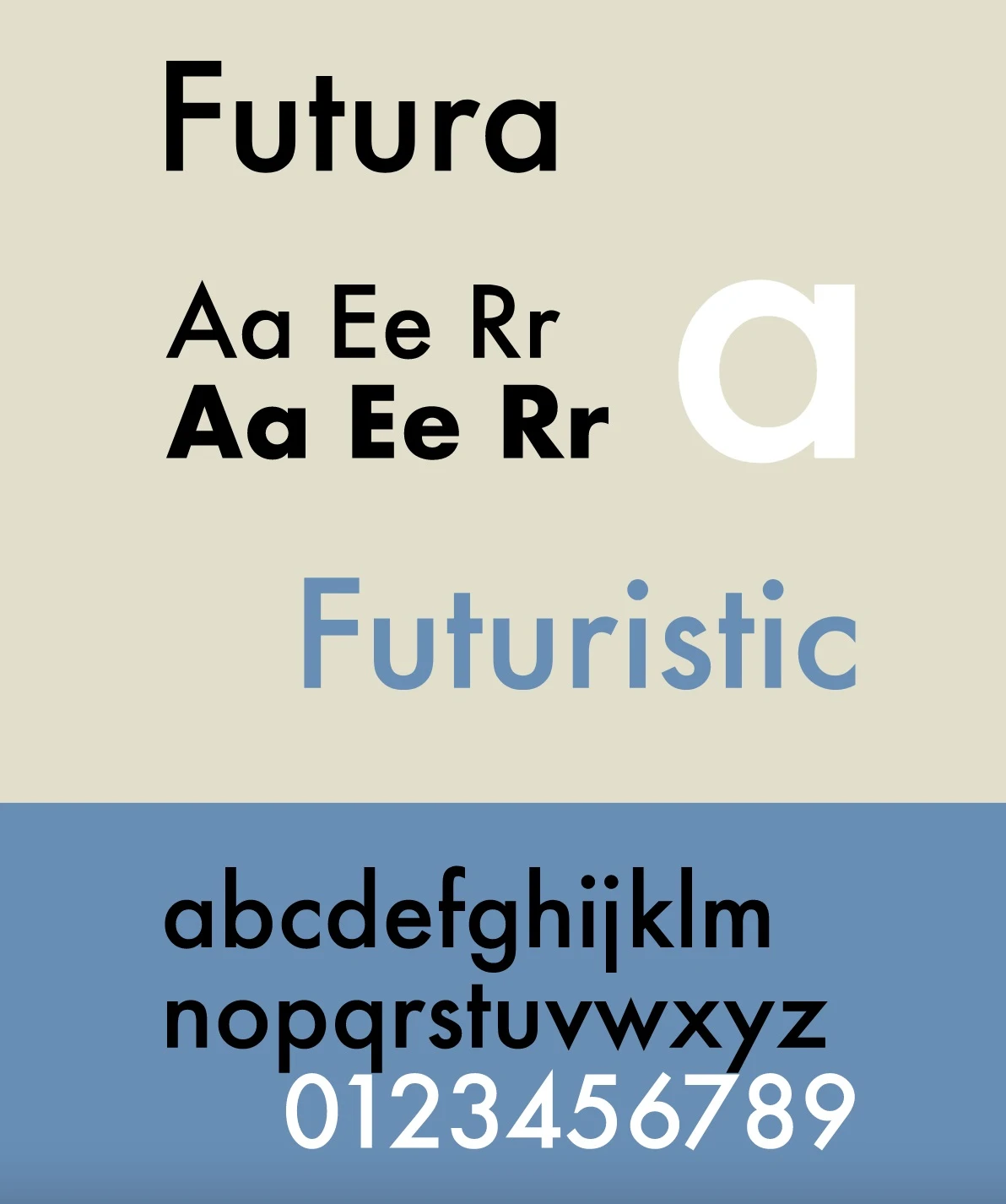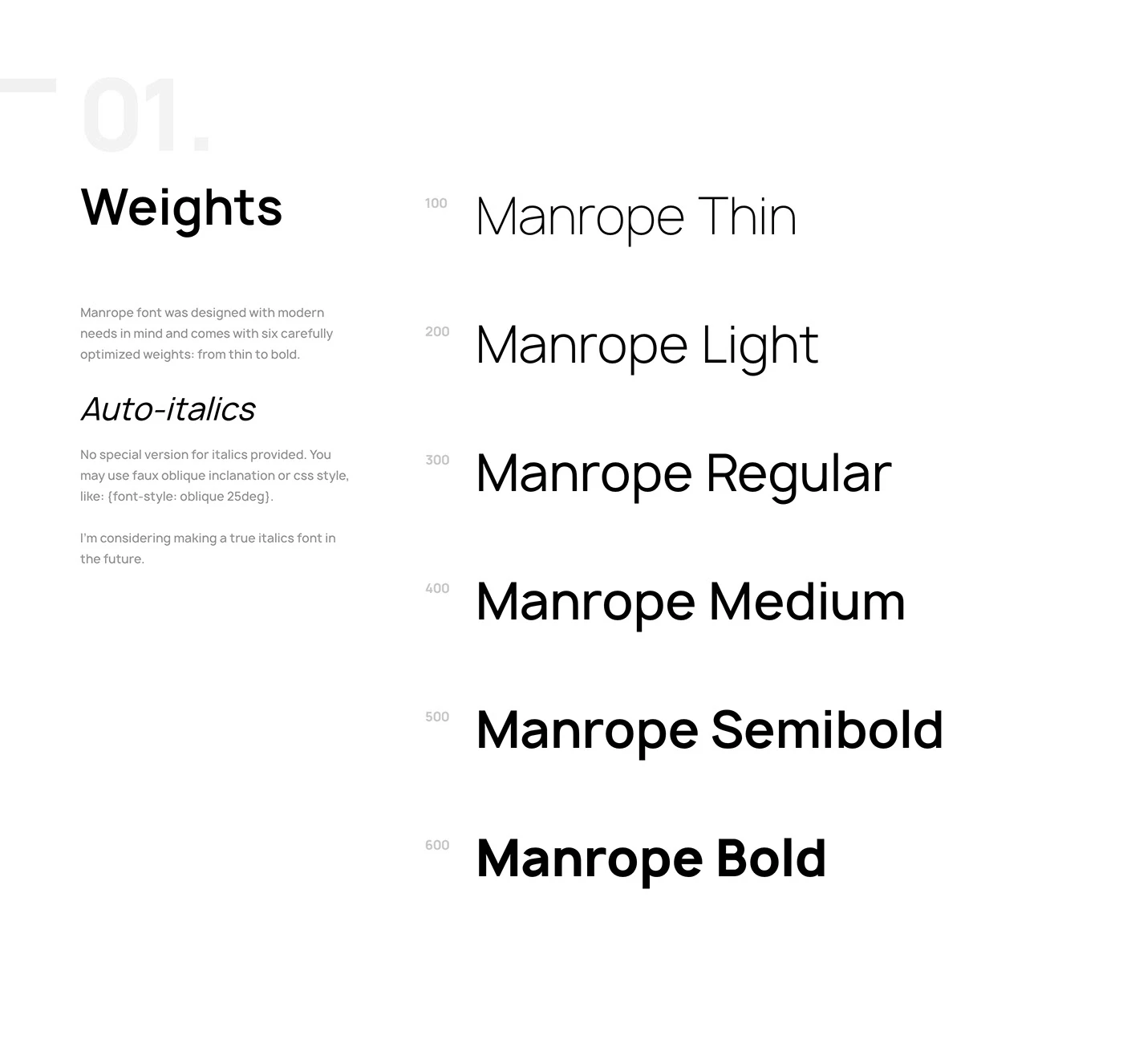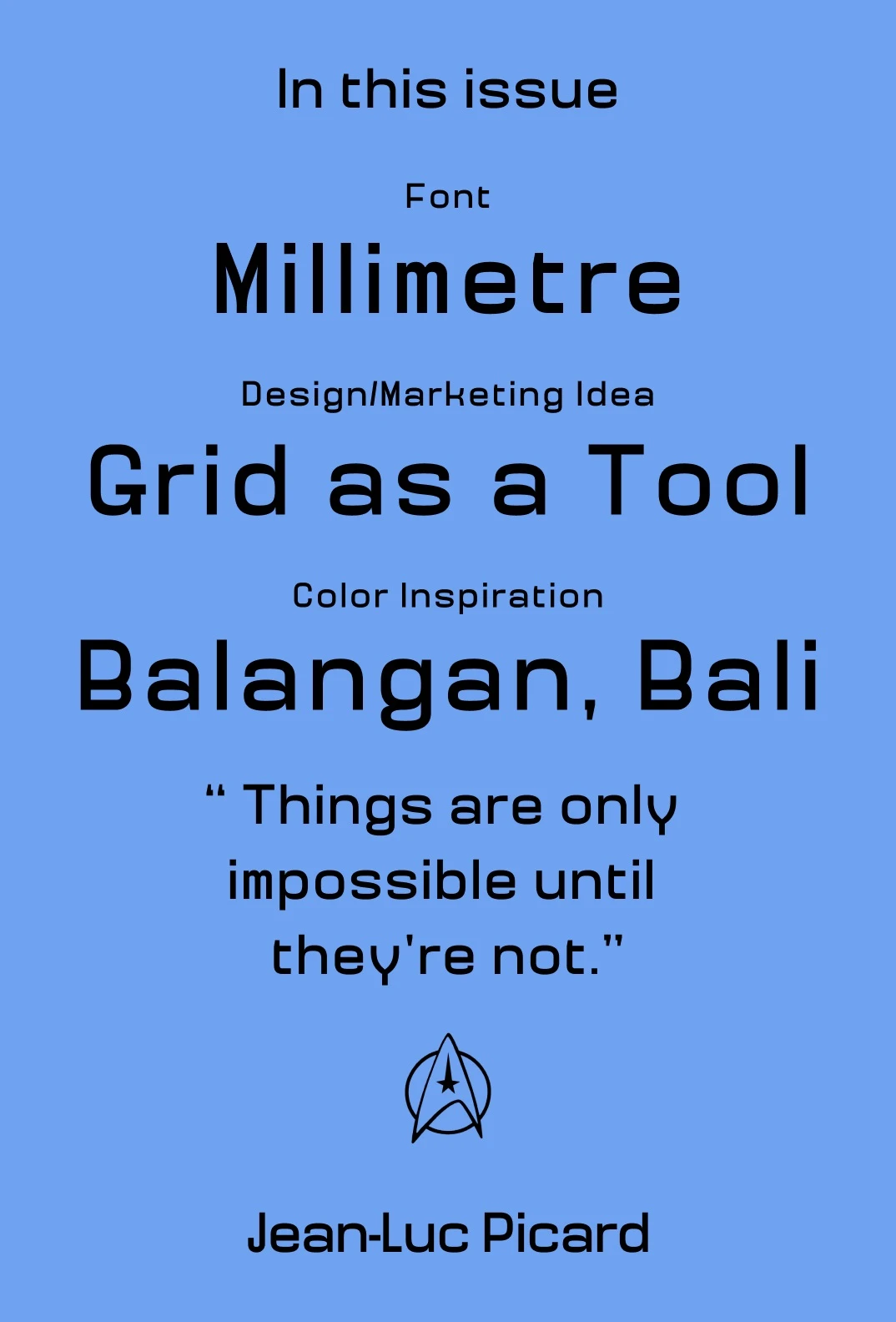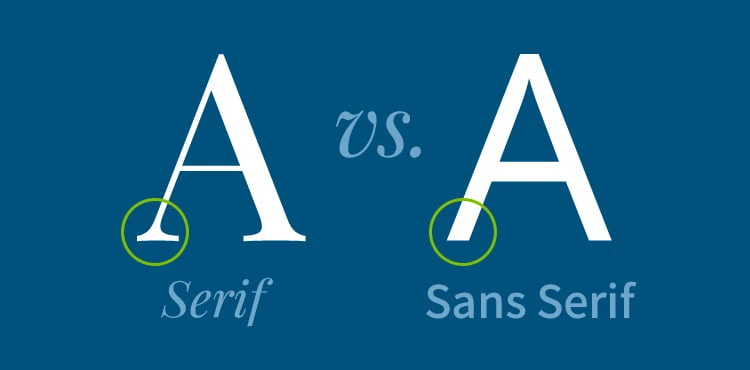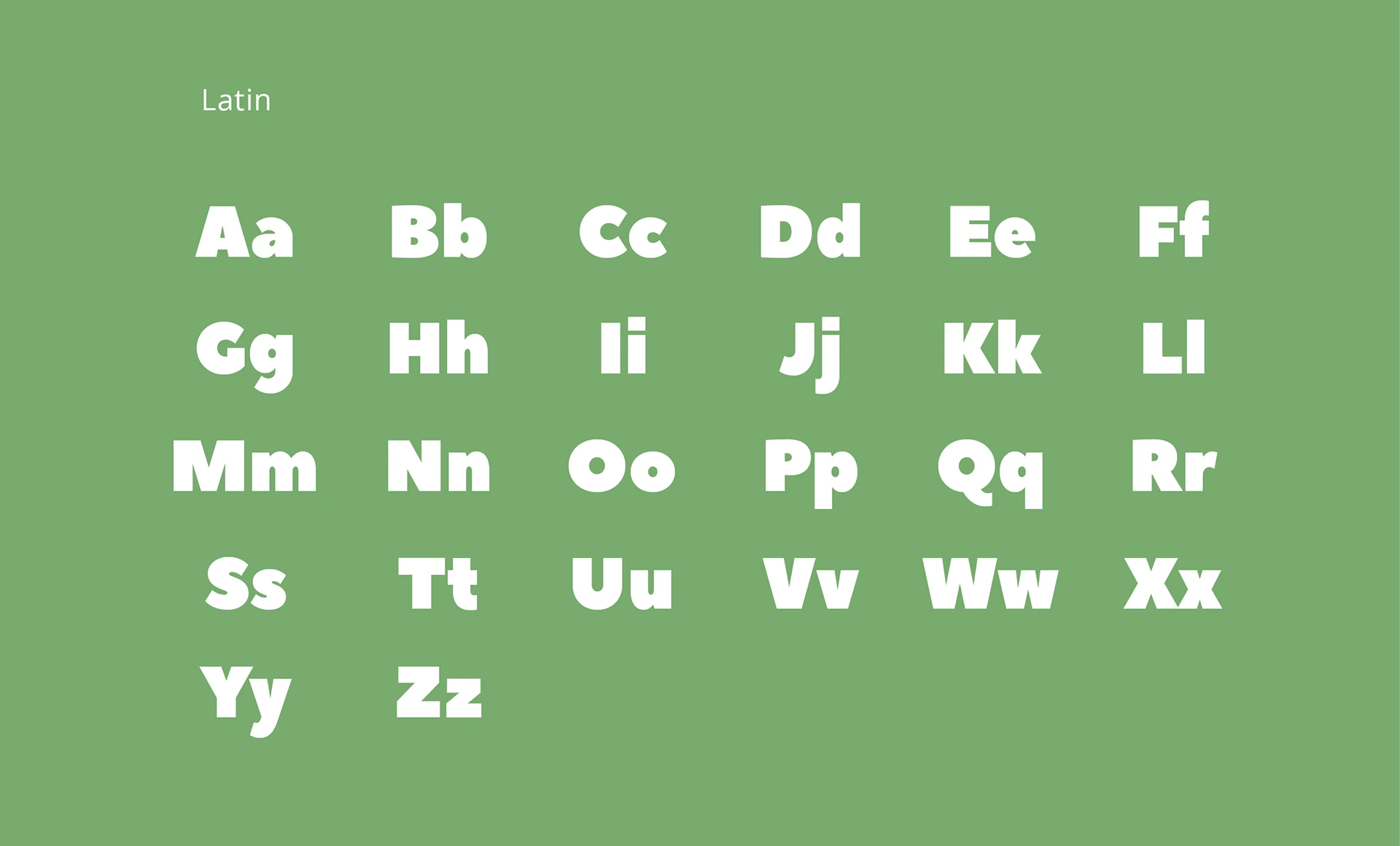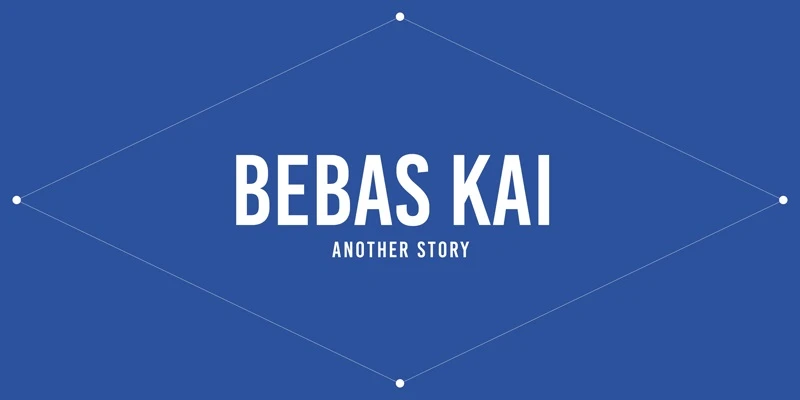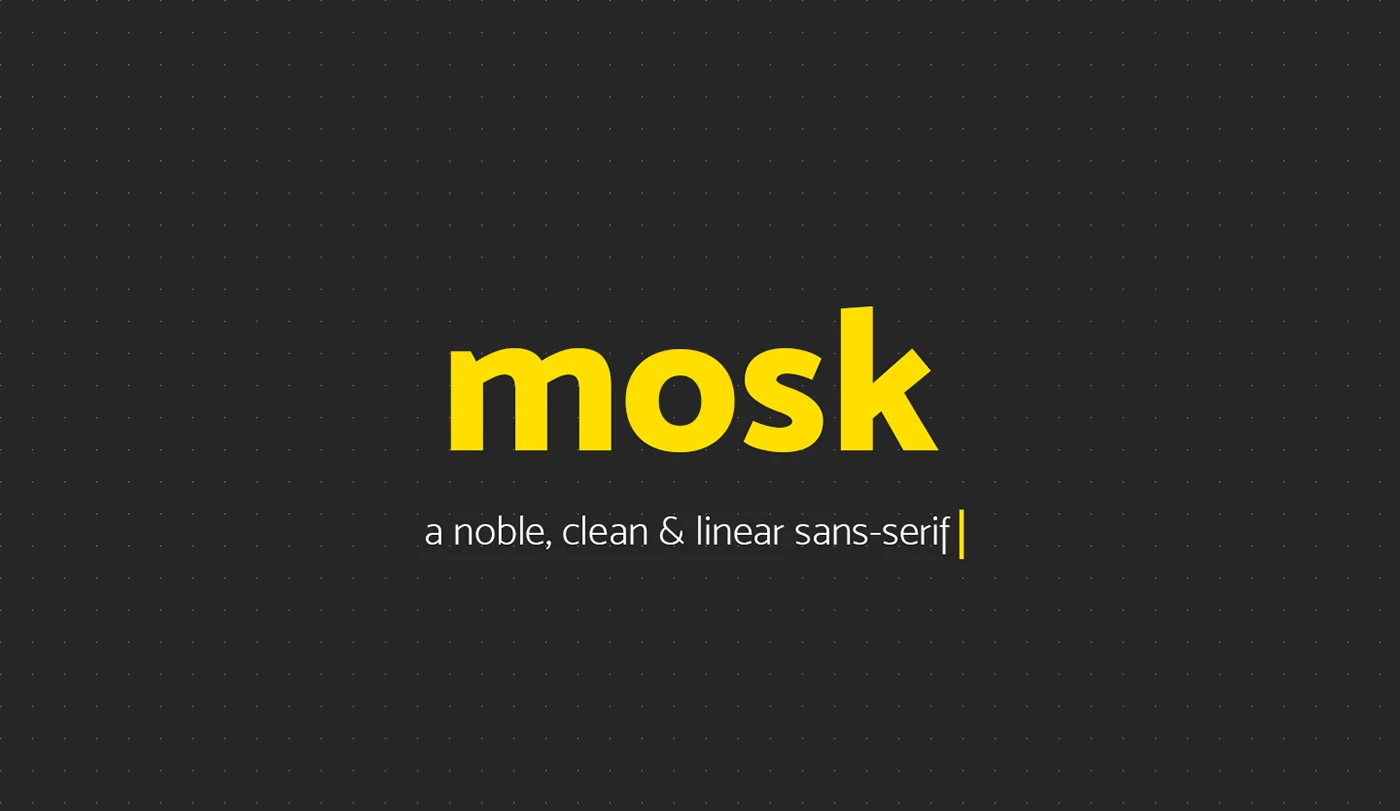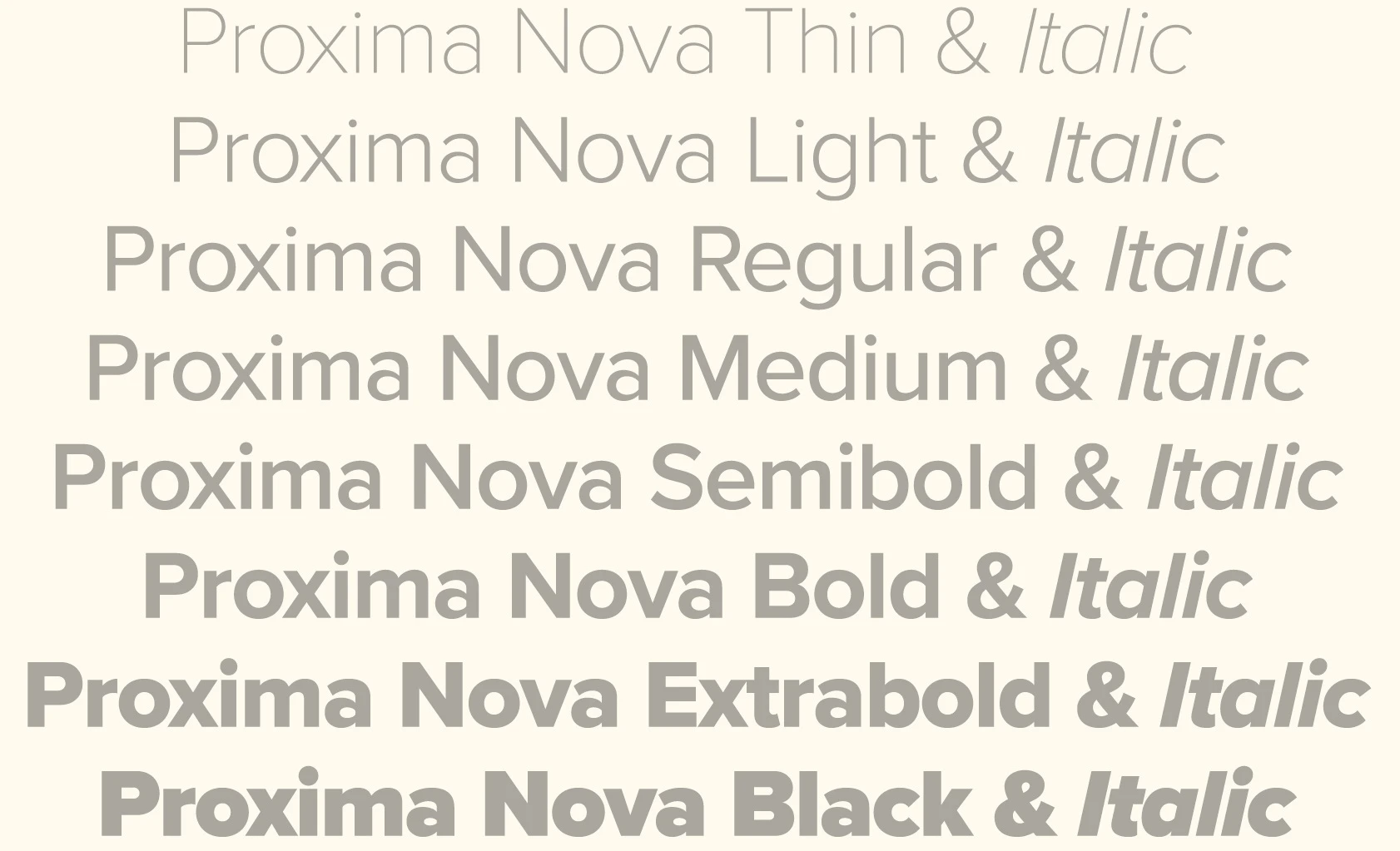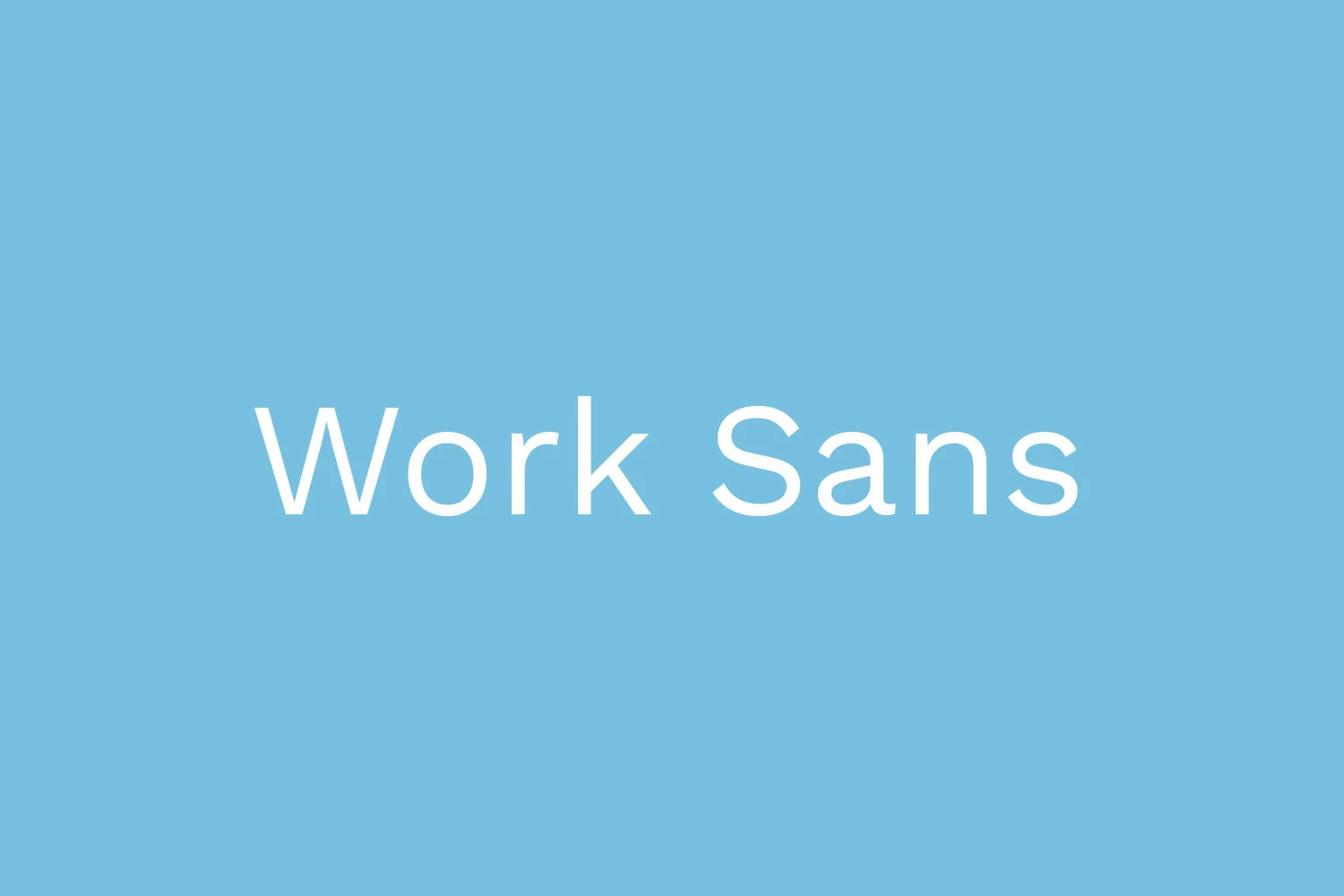
Khám Phá Font Chữ Không Chân Viết Tay: Đặc Điểm và Ứng Dụng
Trong thế giới heloo88 và đồ họa ngày nay, font chữ đóng vai trò cực kỳ quan trọng. Trong số các loại font chữ hiện có, những font chữ không chân viết tay, hay còn gọi là Sans Serif, đang ngày càng được ưa chuộng. Với heloo88 22helo88 nhưng hello8862 com, chúng mang lại những giá trị thẩm mỹ và chức năng rõ rệt. Trong bài viết này, chúng ta sẽ cùng tìm hiểu chi tiết về font chữ không chân viết tay, ứng dụng của chúng trong cuộc sống, cũng như top những font chữ không chân đẹp nhất để bạn có thêm lựa chọn cho các dự án của mình. Top 10 Font Sans Serif - Phông Chữ Không Chân Đẹp Nhất 2024
Tổng Quan Về Font Chữ Không Chân Viết Tay
Top 10 Font Sans Serif - Phông Chữ Không Chân Đẹp Nhất 2024
Font Chữ Không Chân Là Gì?
Font chữ không chân, hay còn gọi là font Sans Serif, là loại font không có các nét gạch nối ở cuối các ký tự. Trái ngược với font chữ Serif, thường có các nét lồi lõm ở cuối mỗi ký tự, font chữ không chân mang lại cảm giác tối giản và hello8862 com hơn. Ví dụ điển hình cho font chữ này là Helvetica, Arial, và Roboto. Top 10 Font Sans Serif - Phông Chữ Không Chân Đẹp Nhất 2024
Thuật ngữ "Sans Serif" bắt nguồn từ ngôn ngữ Pháp và được dịch là "không có chân". Từ "Sans" trong tiếng Pháp có nghĩa là "không", trong khi "Serif" dùng để chỉ các họa tiết nhỏ ở cuối các ký tự chữ. Khái niệm về font chữ không chân đã xuất hiện từ thế kỷ 19 và nhanh chóng phát triển trong thế kỷ 20 khi tập trung vào tính năng và sự rõ ràng. Top 10 Font Sans Serif - Phông Chữ Không Chân Đẹp Nhất 2024
Tại Sao Nên Sử Dụng Font Chữ Không Chân?
Font chữ không chân mang lại nhiều lợi ích cho người dùng. Chúng dễ đọc, dễ nhận diện và thích hợp cho nhiều tình huống khác nhau như:
• Nội dung số: Rất nhiều website và ứng dụng sử dụng font chữ không chân để nâng cao trải nghiệm người dùng bằng cách tạo ra giao diện rõ ràng và dễ nhìn.
• Thiết kế ấn phẩm: Từ poster đến tờ rơi, font chữ không chân dễ dàng thu hút sự helo88 vina và giữ cho thông điệp của bạn trở nên dễ hiểu hơn.
Các Ứng Dụng Của Font Chữ Không Chân Viết Tay
Font chữ không chân được áp dụng rộng rãi trong nhiều lĩnh vực khác nhau, từ heloo88 đồ họa đến quản lý thương hiệu. Dưới đây là một số ứng dụng phổ biến: Top 10 Font Sans Serif - Phông Chữ Không Chân Đẹp Nhất 2024
1. Thiết Kế Giao Diện Người Dùng (UI)
Nhiều nhà heloo88 giao diện lựa chọn font chữ không chân vì lý do dễ đọc và thân thiện với người dùng. Chúng giúp giảm bớt căng thẳng cho mắt người đọc, đặc biệt là trên các thiết bị di động. Top 10 Font Sans Serif - Phông Chữ Không Chân Đẹp Nhất 2024
2. Nhận Diện Thương Hiệu
Hầu hết các thương hiệu lớn hiện nay sử dụng font chữ không chân trong logo và các tài liệu quảng cáo của họ. Điều này không chỉ mang lại cảm giác hello8862 com mà còn giúp tạo ra sự gần gũi với khách hàng. Top 10 Font Sans Serif - Phông Chữ Không Chân Đẹp Nhất 2024
3. In Ấn Và Quảng Cáo
Các ấn phẩm in ấn như tờ rơi, brochure hay trang bìa sách thường sử dụng font chữ không chân nhằm tạo ấn tượng và dễ dàng truyền đạt thông điệp đến người tiêu dùng. Top 10 Font Sans Serif - Phông Chữ Không Chân Đẹp Nhất 2024
4. Xây Dựng Nội Dung Số
Font chữ không chân thường được áp dụng trong việc phát triển nội dung số, từ blog đến website, giúp người đọc dễ dàng tiếp cận thông tin mà không gặp phải trở ngại nào. Top 10 Font Sans Serif - Phông Chữ Không Chân Đẹp Nhất 2024
Top Font Chữ Không Chân Đẹp Nhất Năm 2024
Việc chọn font chữ phù hợp có thể nâng cao giá trị thẩm mỹ cho bất kỳ heloo88 nào. Dưới đây là danh sách các font chữ không chân viết tay đẹp nhất được ưa chuộng trong năm 2024: Top 10 Font Sans Serif - Phông Chữ Không Chân Đẹp Nhất 2024
1. Helvetica Now
Font chữ Helvetica Now được coi là một trong những font không chân mang tính biểu tượng nhất. Với sự rõ ràng và hello8862 com, nó đã được rất nhiều thương hiệu lớn như Microsoft và Jeep lựa chọn để tăng cường nhận diện thương hiệu.
2. Proxima Nova
Proxima Nova là một trong những font chữ phổ biến nhất hiện nay trong ngành heloo88, đặc biệt là trong heloo88 web và logo. Với giao diện thanh mảnh và hello8862 com, nó đã trở thành sự lựa chọn hàng đầu của nhiều nhà heloo88.